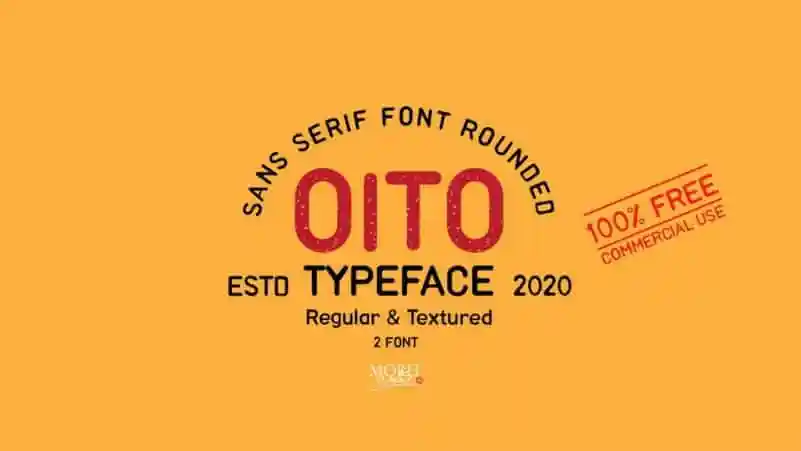
Oito Display Font Family – Download Grátis
A fonte “Oito Display Font Family” oferece uma experiência visual única para designers e criativos do Brasil. Com seu estilo vintage, a fonte é ideal para projetos que buscam um toque de elegância, sejam eles logotipos, badges, painéis ou qualquer outro projeto com um apelo nostálgico. Feita pelo designer da 99designs Morel Graphic, Oito apresenta duas estilos distintos: Regular e Textured. Essencialmente simples e divertida, a fonte consegue incorporar uma personalidade natural aos seus textos. Suas linhas elegantes são projetadas para criar um efeito vintage, mantendo ao mesmo tempo um ar descontraído que combina perfeitamente com as necessidades atuais dos designers digitais brasileiros. Perfeita para quem busca deixar seu trabalho ainda mais memorável e atraente, Oito é uma escolha sólida e versátil no mercado de fontes modernas do Brasil.